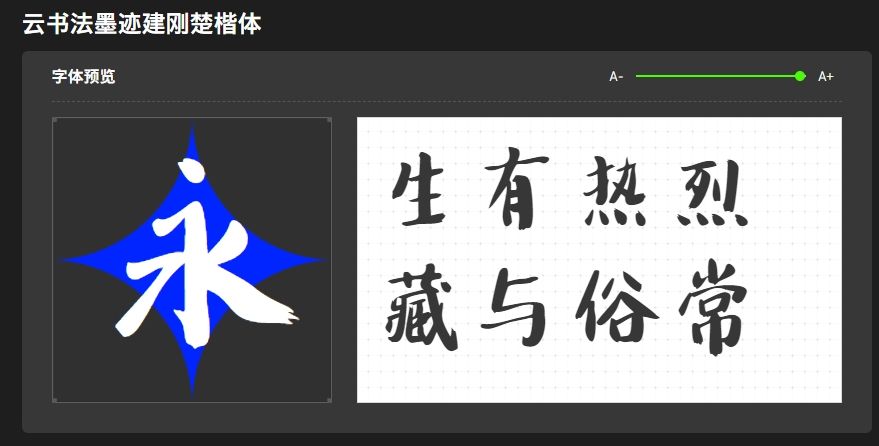
复古韵味的楷体,让字体焕发历史的光彩!
楷体,作为中国传统书法的一种表现形式,以其古朴典雅的风格,深受人们的喜爱。在字体设计中,楷体以其独特的韵味,为文字注入了历史的厚重感。
楷体字体具有浓厚的复古气息,每一笔一划都仿佛承载着千年的文化积淀。它的线条粗细有致,结构严谨,既展现了书法的神韵,又适应了现代设计的需要。
云书法墨迹建刚楚楷体,字体字形飘逸、方正,笔画和部首均衡分布、重心平稳、比例适当、字形端正,笔锋细腻,整体效果非常出色。
同时,楷体字体在排版上也具有极高的灵活性。无论是横排还是竖排,都能保持其独特的风格特点,为设计师提供了更多的创作空间。
因此,如果你希望让文字焕发历史的光彩,那么楷体无疑是一个值得尝试的选择。